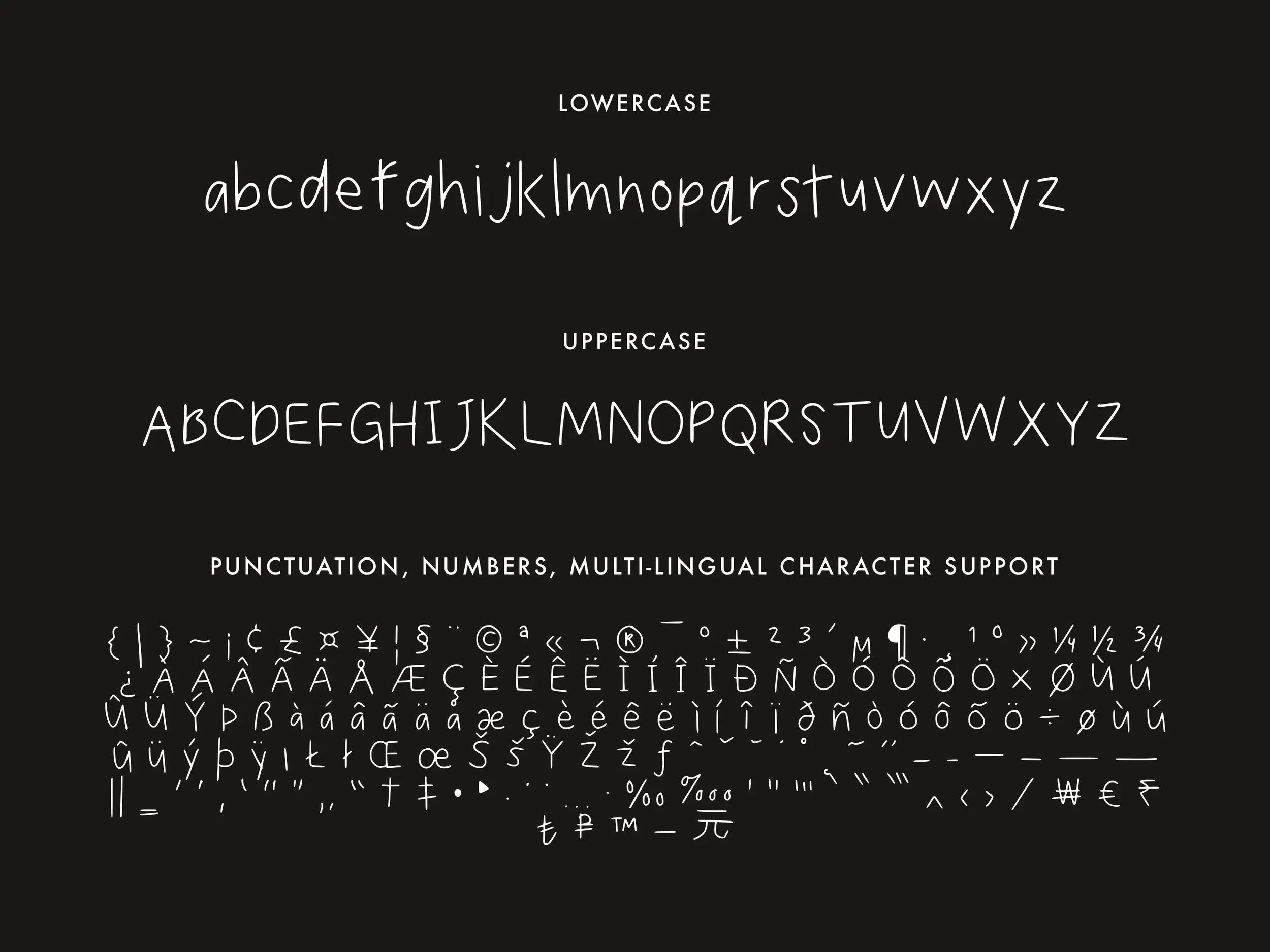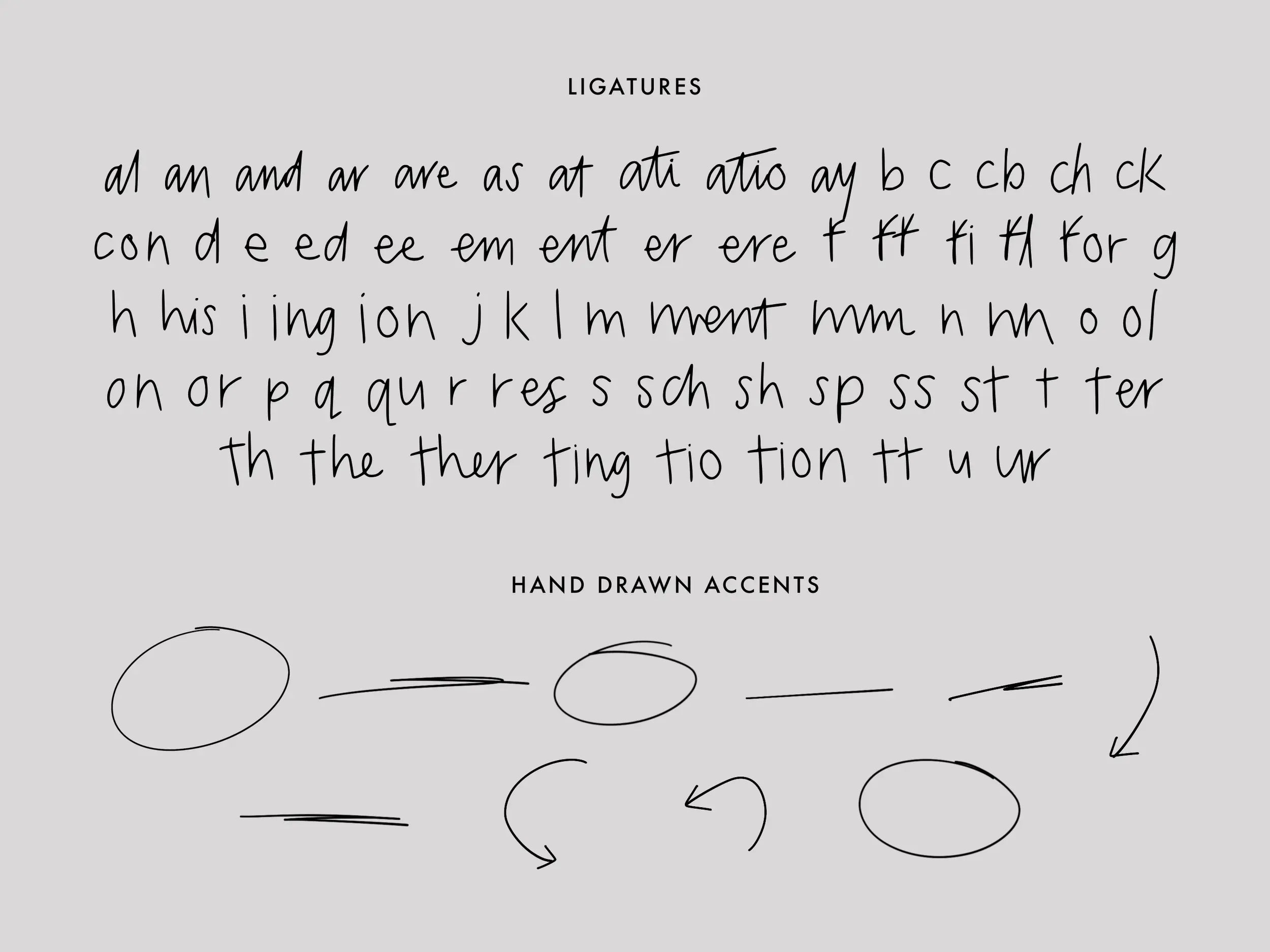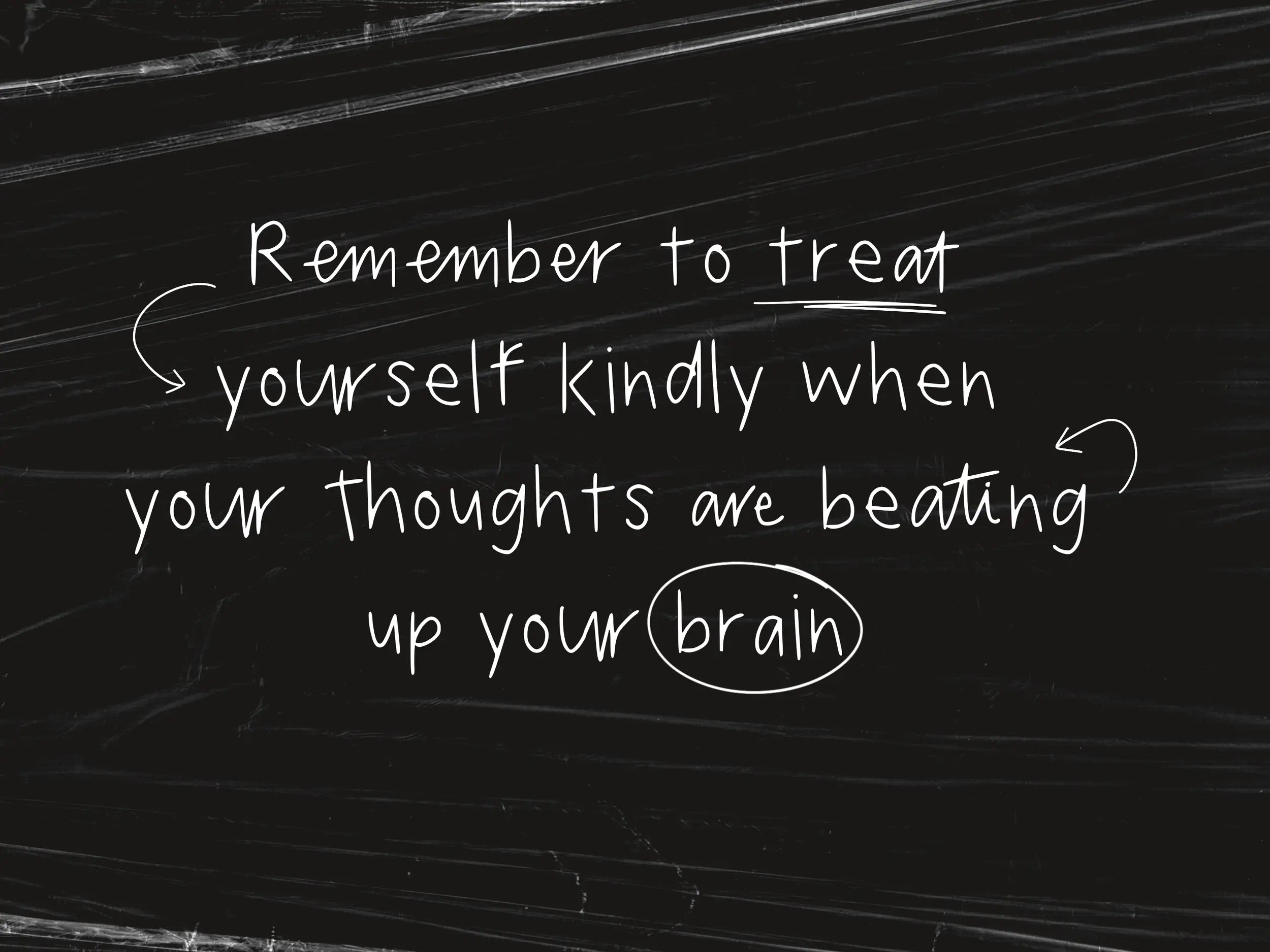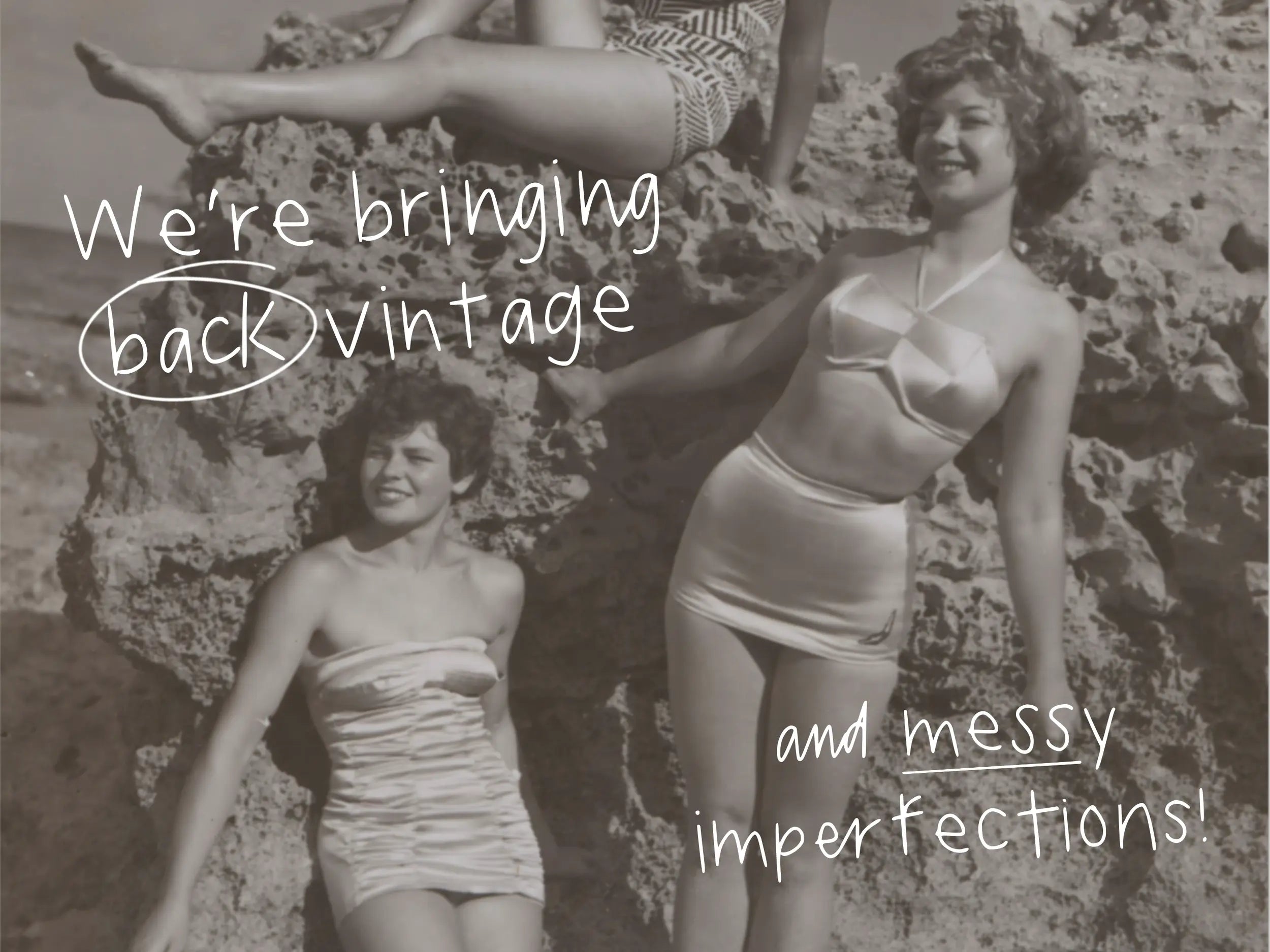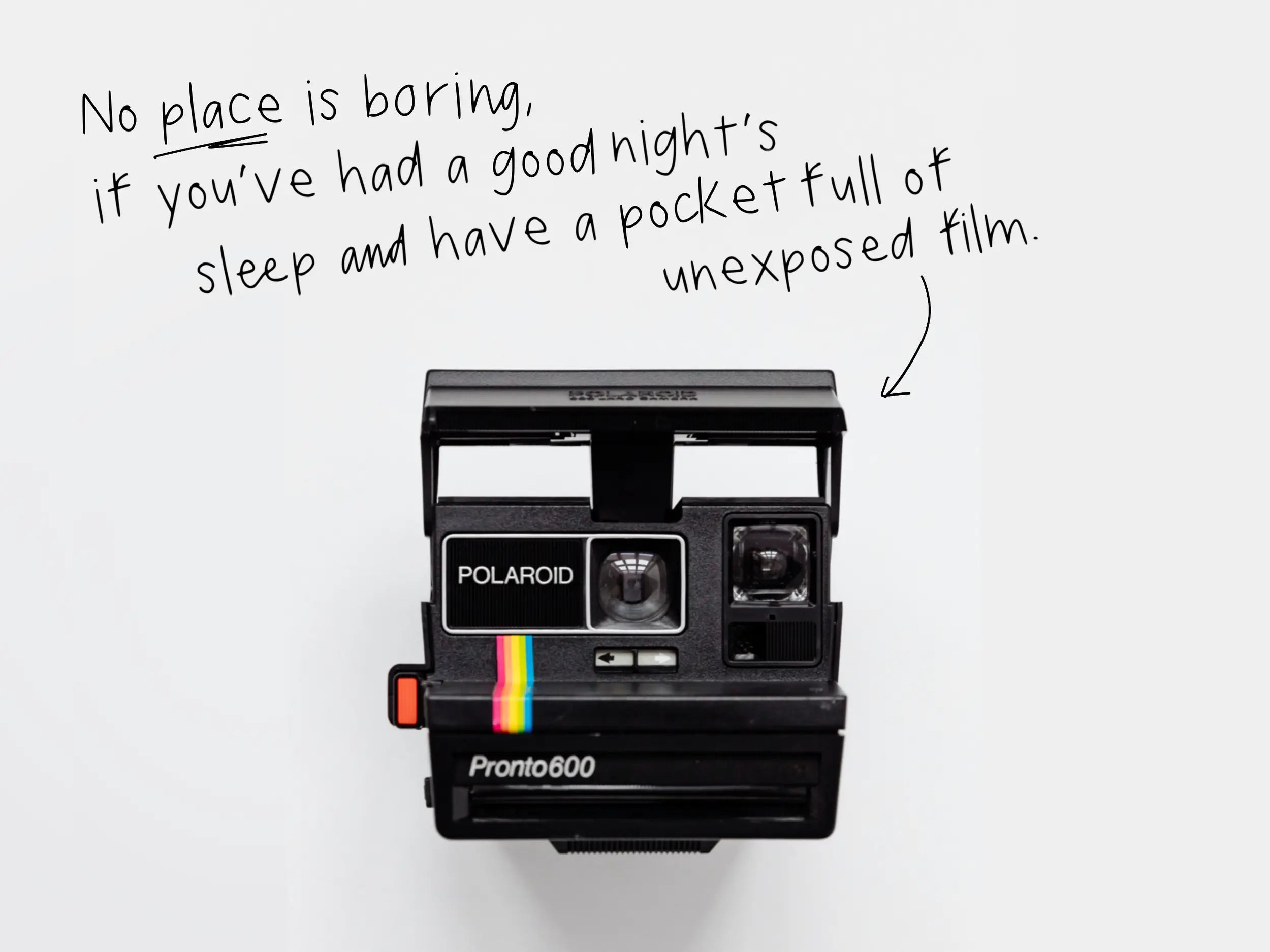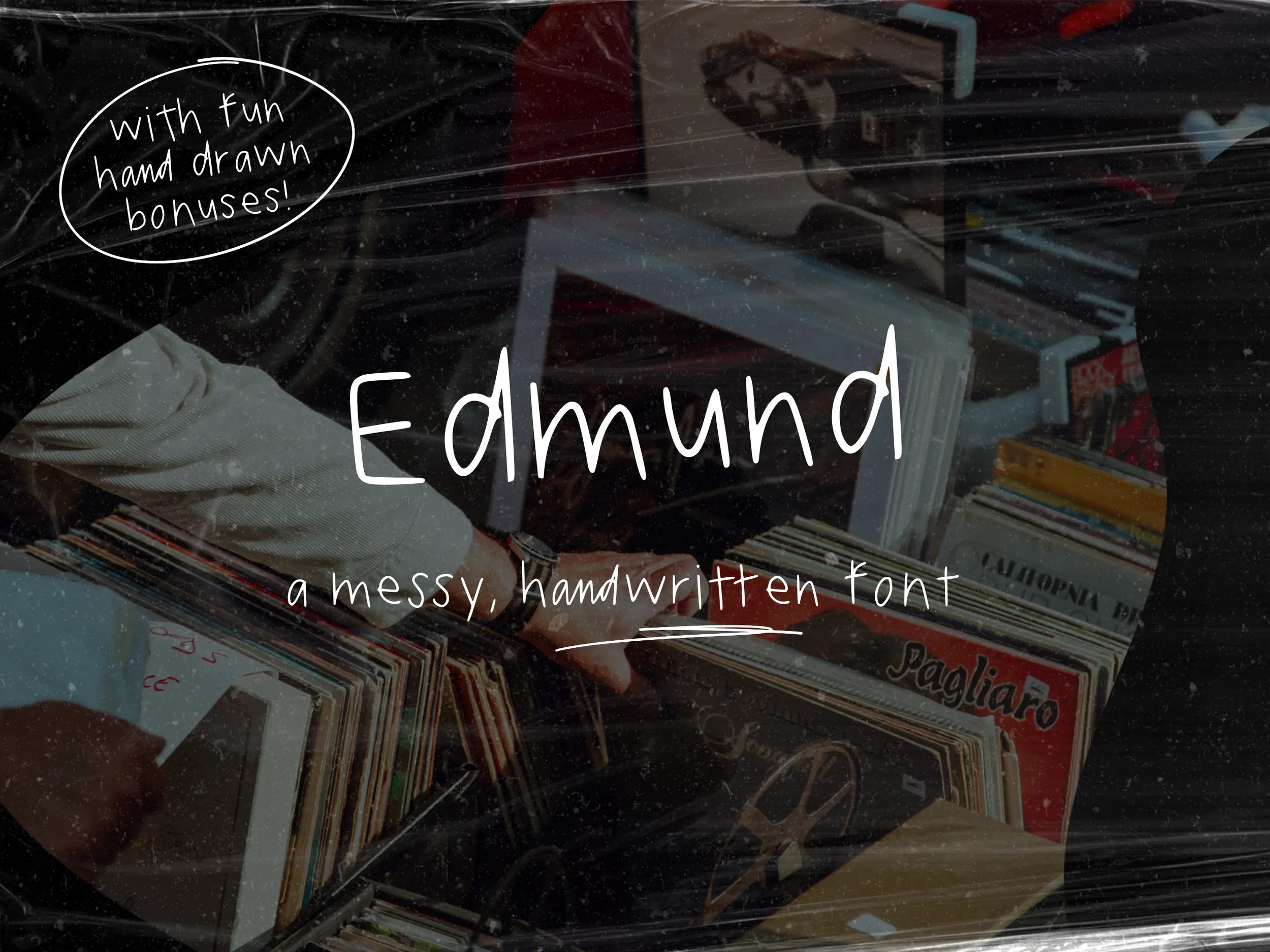
Edmundo Fuente
Edmund: una fuente manuscrita, desordenada y con mucho carácter. Excelente para crear publicaciones de citas de Instagram, invitaciones y papelería para compartir, y mucho más.